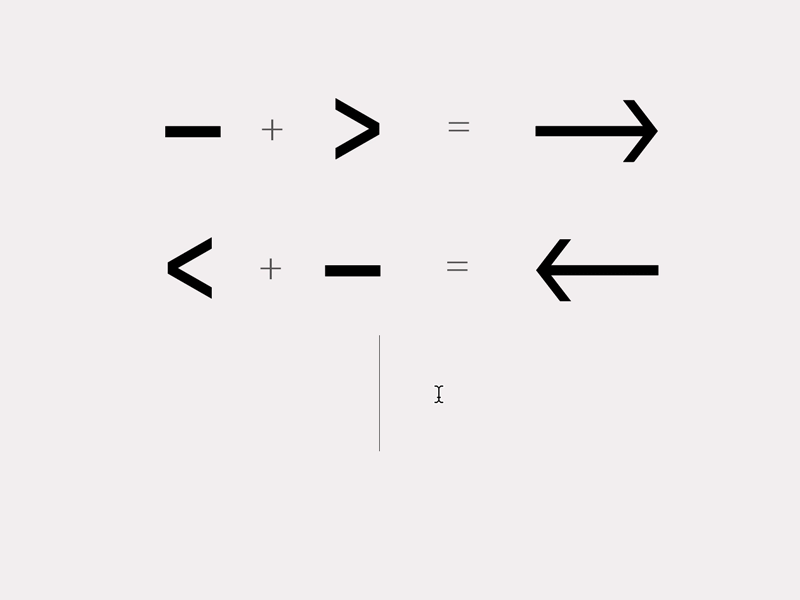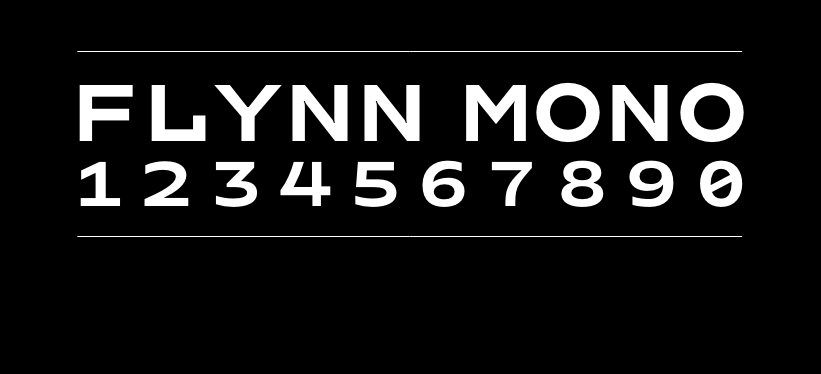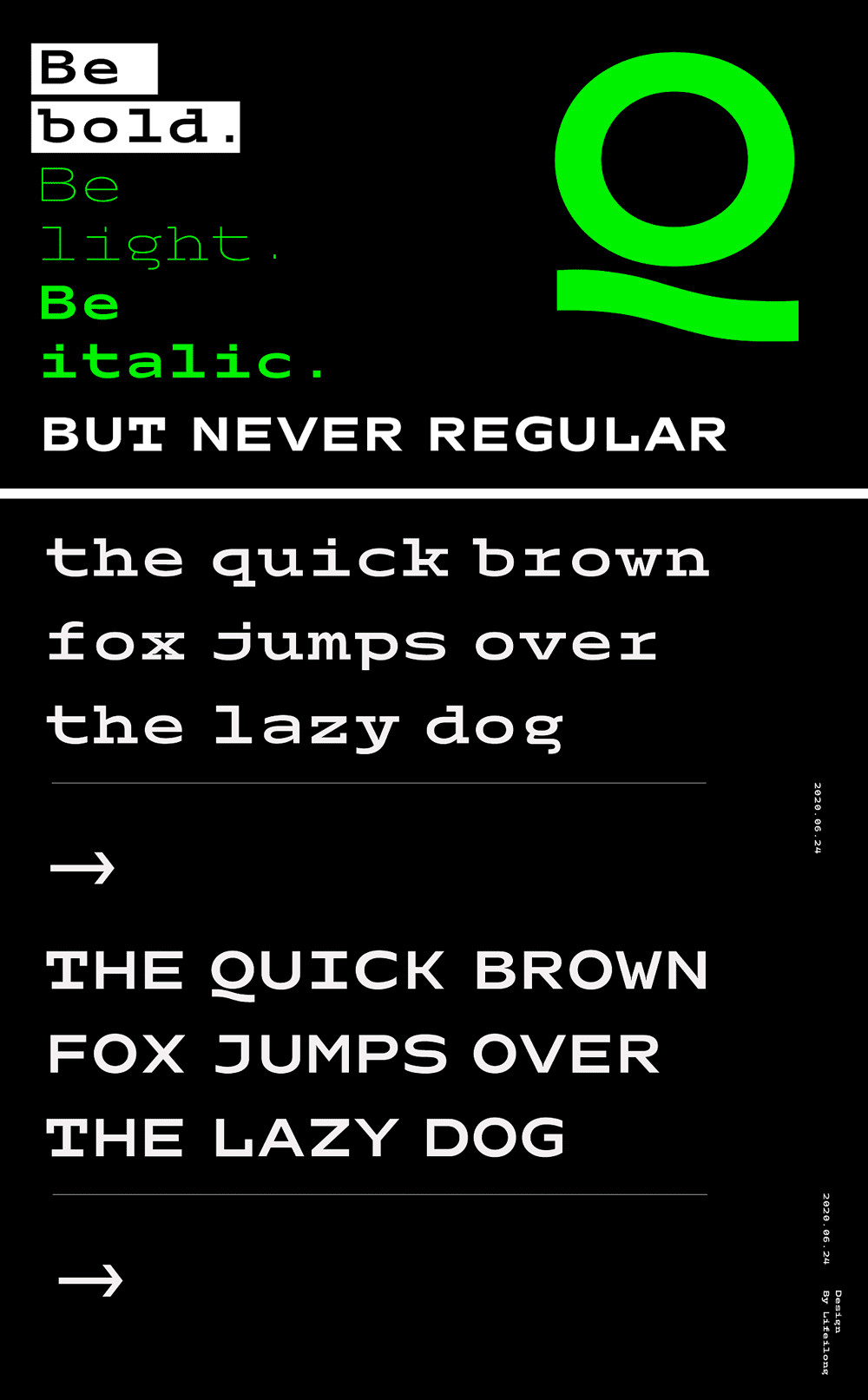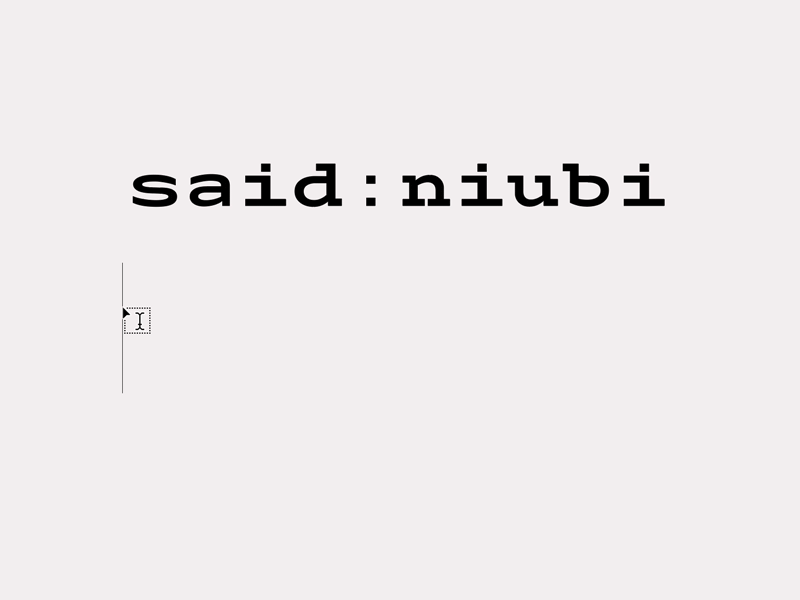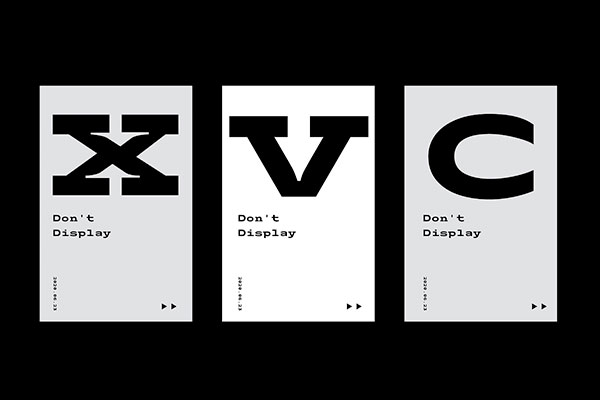
字体下载 Flynn Mono
Flynn Mono
Flynn Mono是一款等宽西文字体,作者是北京的设计师李扑通。作者自称造型比较怪异,加个比较夸张的屏显化处理,但并不适合用做正文阅读,也不适合拿来敲代码用,主要还是想研究下Opentype features以及和大家一起交流下可变字体。
该字体包含4个字重,并附带一个vf可变字体文件,在支持的可变字体的软件中,输入部分字符可以会有一些效果变化。具体可以看下面的动图展示。
Flynn Mono